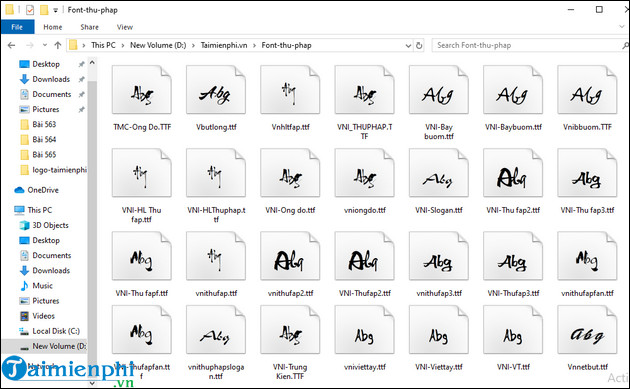
Font Thư Pháp
Download Font Thư Pháp - Hỗ trợ viết thư pháp, câu đối đẹp
1. Giới thiệu về Font chữ Thư Pháp
Sử dụng font thư pháp mang lại nhiều lợi ích, đặc biệt là trong lĩnh vực thiết kế và truyền thông nhờ vào sự độc đáo và tính nghệ thuật. Với đa dạng mục đích sử dụng, font chữ này cũng được sử dụng trong nhiều ngữ cảnh khác nhau, từ công việc sáng tạo đến trình bày văn bản học thuật.
Sáng tạo những bức tranh, câu đối đẹp mắt với font chữ thư pháp
2. Những Font Thư Pháp Việt Hóa đẹp nhất
- VNI QUANG NINH: Bộ font chữ đơn giản, dễ đọc, với các nét đậm và nhạt được thiết kế bởi tác giả Quang Ninh.
- VNIThufapfan: Phông có các nét chữ rõ ràng, được sử dụng phổ biến trong thiết kế.
- TMC- Ong Do: Font có nét chữ đậm nhưng vẫn toát lên sự sang trọng, thường được sử dụng trong viết câu thơ và văn đối.
- VNIHLThuphap: Font thuộc loại cổ điển, thường xuất hiện trên các bảng hiệu và quán cà phê hoài cổ.
- VNIBaybuom: Phông có các dòng chữ lệch nhau, không thẳng hàng, tạo điểm độc đáo và nổi bật.
- Thufap02: Font được sử dụng phổ biến trong thiệp mời với nét chữ hài hòa và dễ đọc.
- VNI Trung Kiên: Phông tận dụng các ký tự ít sử dụng trên bàn phím để tạo ra các ký tự mới, mang lại cảm giác "hàng thật".
- UTM Thiên Ân: Font được thiết kế chủ yếu cho các designer và người sử dụng Corel hoặc Illustrator.
- HL Thuphap 4BK: Phông có nét chữ cứng nhưng dễ đọc, thích hợp sử dụng ở nhiều trường hợp.
- Công Thủy: Font được sử dụng phổ biến trong việc trang trí, thiết kế thiệp cưới và thiệp xuân.